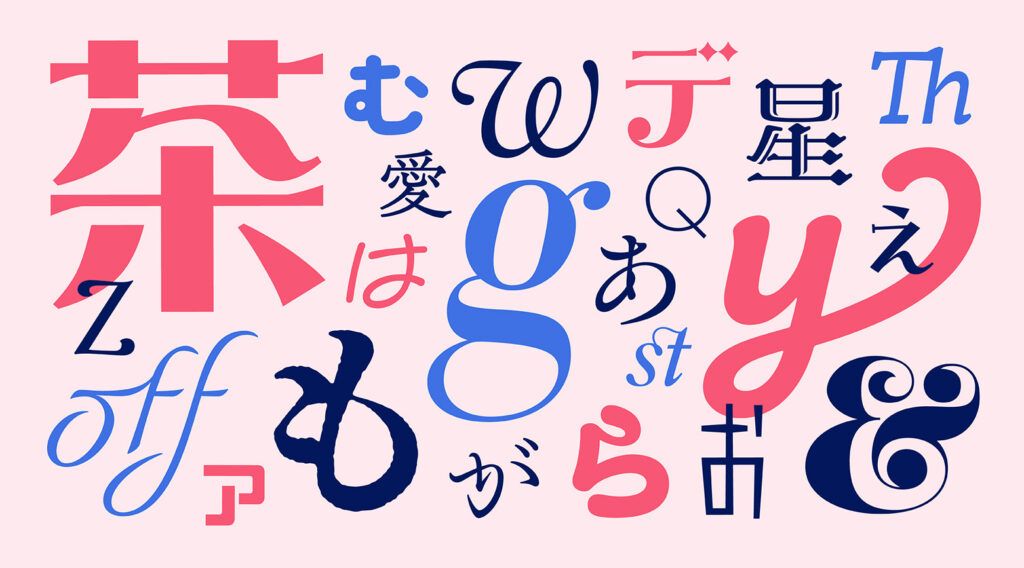
モリサワ 2022年新書体をMorisawa FontsおよびMORISAWA PASSPORT製品にて提供開始
株式会社モリサワは、10月26日より、Morisawa FontsおよびMORISAWA PASSPORT製品を契約中の顧客先に対して、「アップグレード2022年10月版」の提供を開始した。
今回のアップグレードで追加される書体は、 和文・欧文の新書体77ファミリーと、 既存書体の総合書体化やAP版書体の28ファミリー。
和文書体は、『インパクト』『ゆるポップ』『ロマン』『オールド』の4ジャンルにわたり、 さまざまなバリエーションのデザインとなっている。
雷鳴で割れたような端々の装飾がパワフルな迫力を与える書体「イカヅチ」や、 筆ペンで書いた文字をイメージしたゆる可愛い書体「ぽってり」、 ひと目見ただけでレトロかつ華やかな印象を与える「白のアリス」「オズ」、 筆や活字の雰囲気を残したクラシカルな印象の「霞青藍」「霞白藤」など、 多彩な印象のデザイン書体が一挙に追加された。
「文游明朝体」と共通の漢字デザインをもつ別かなシリーズには「古雅かな」「朝靄かな」「水面かな」の3書体を追加し、繊細な表情の違いが楽しめるようになるほか、活版印刷による紙面上でのインクのにじみを再現した「秀英にじみ四号太かな」や、総合書体化された「秀英四号太かな+」、ユニークで個性的な丸ゴシック体「ヒラギノ丸ゴ オールド」なども登場する。
さらに欧文書体も『オーガニック&ディスプレイ』『クラシカル&スタンダード』『Roleスーパーファミリー』『Clarimo UDシリーズ』の4ジャンルで49ファミリーを提供。欧文書体の選択肢が広がり、多言語併記が必要な場面でも豊かなデザインを可能にする。
シャープで流麗なストロークがフォーマルな印象を与える「Abelha Pro」、“カリグラフィの要素” を取り入れた字形で華やかなニュアンスが出る「Letras Oldstyle Pro」、200書体を誇る『Roleスーパーファミリー』など見出し用途に使いやすい書体から汎用性の高い書体まで幅広いバリエーションが揃っている。
また、UD新ゴとの併記を目的に開発された『Clarimo UDシリーズ』のコンデンス(長体)展開は、多言語をカバーする「UD新ゴ」シリーズと高い親和性を発揮する。